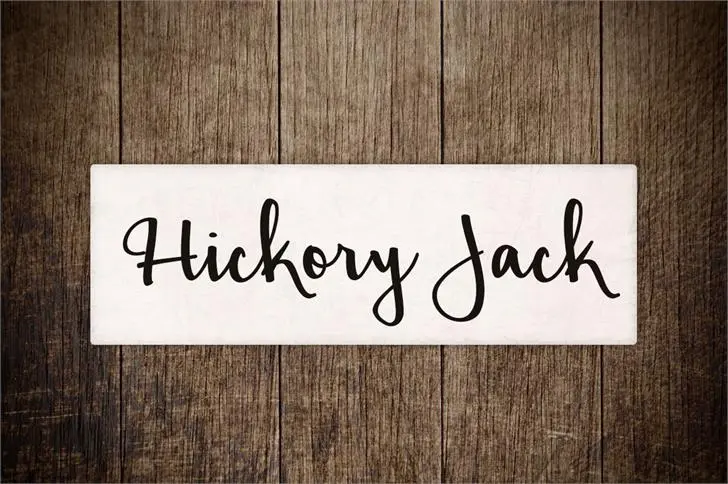
Hickory Jack font – Download Grátis
A Hickory-Jack é uma fonte escrita a mão criada em 2016 pela Brittney Murphy Design. Com traços leves e textura natural, esta fonte retrata um estilo de escrever com autenticidade, ideal para trabalhos que valorizam personalidade e expressão única. Se você busca uma fonte que reflete a elegância do estilo manuscrito mais intimista, Hickory-Jack é certamente uma opção a ser considerada. Suas linhas finas criam um contraste interessante com suas texturas suaves, tornando-a uma escolha versátil tanto para letras grandes quanto para pequenas detalhes de texto, adaptando-se facilmente às necessidades do design gráfico moderno. Ideal para aqueles que desejam trazer vida e personalidade à sua produção visual, a Hickory-Jack é um verdadeiro presente para os designers amantes da arte manuscrita.